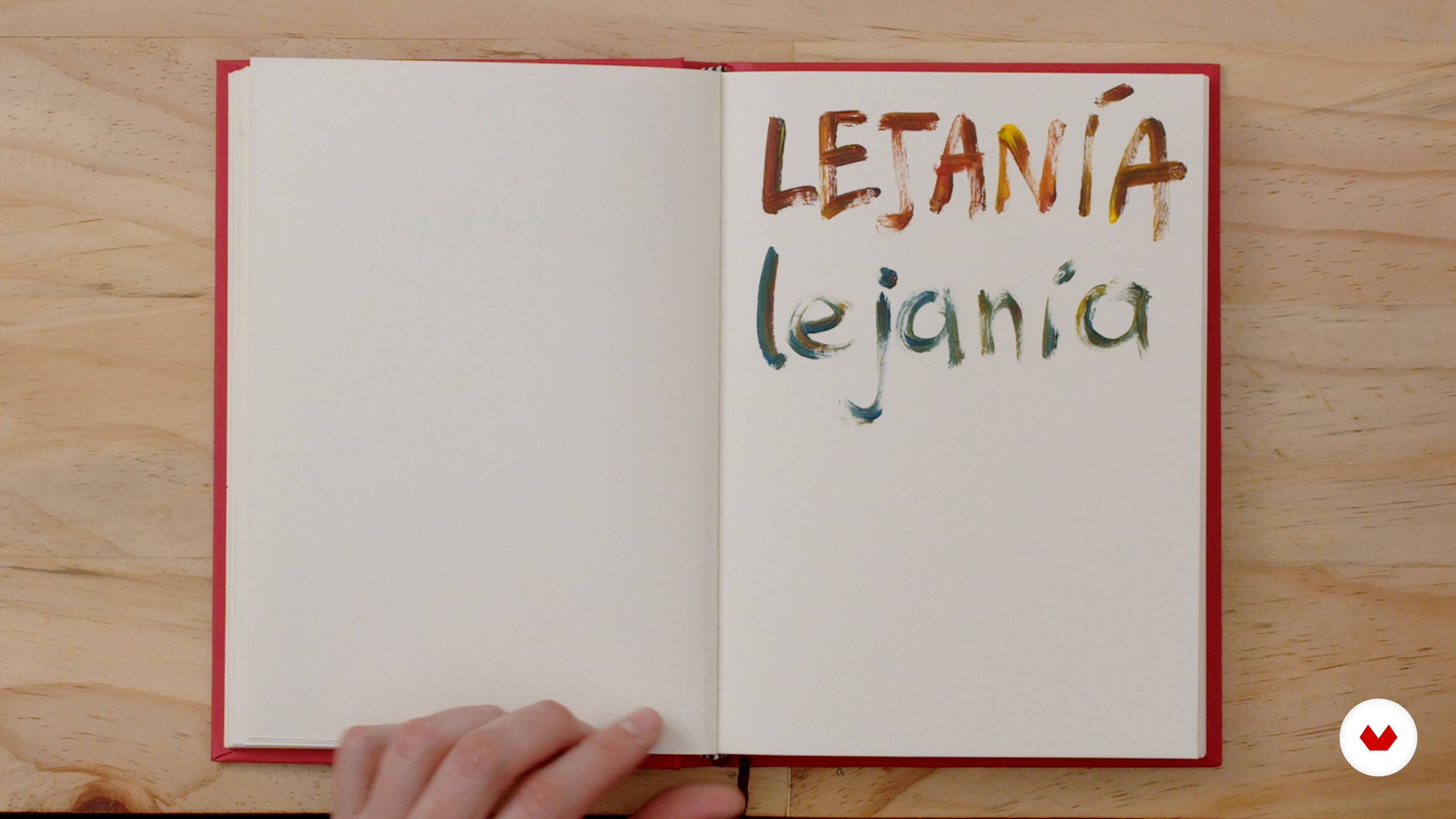
Tipografia
“Ora che abbiamo dipinto completamente il nostro libro, fronte e retro, cercheremo il font appropriato per la sua copertina, il titolo del nostro lavoro, e che lavoreremo anche manualmente. Potremmo cercare fonti che abbiamo caricato sul nostro computer, è totalmente valido, ma in questo caso cercheremo di rendere il risultato finale il più organico e personale possibile. Quindi, proveremo diverse opzioni e selezioneremo quella che meglio si adatta all'argomento su cui abbiamo lavorato. ”
“Tipografia Abbiamo il nostro progetto finale pronto. È completamente dipinto, come abbiamo visto, su entrambi i lati, davanti e dietro. Abbiamo lavorato duramente per raggiungere questo risultato. Ora quello che faremo è un esercizio aggiuntivo, che sta lavorando proprio sulla tipografia del titolo e il nome dell'autore, il tuo nome. Userò gli stessi strumenti che abbiamo usato prima, cosa sono i pennelli, i colori acrilici che abbiamo deciso di utilizzare. Qualcosa che voglio sottolineare qui e che è molto importante è che questa non è sicuramente la mia forza, ma anche così, credo che far...”